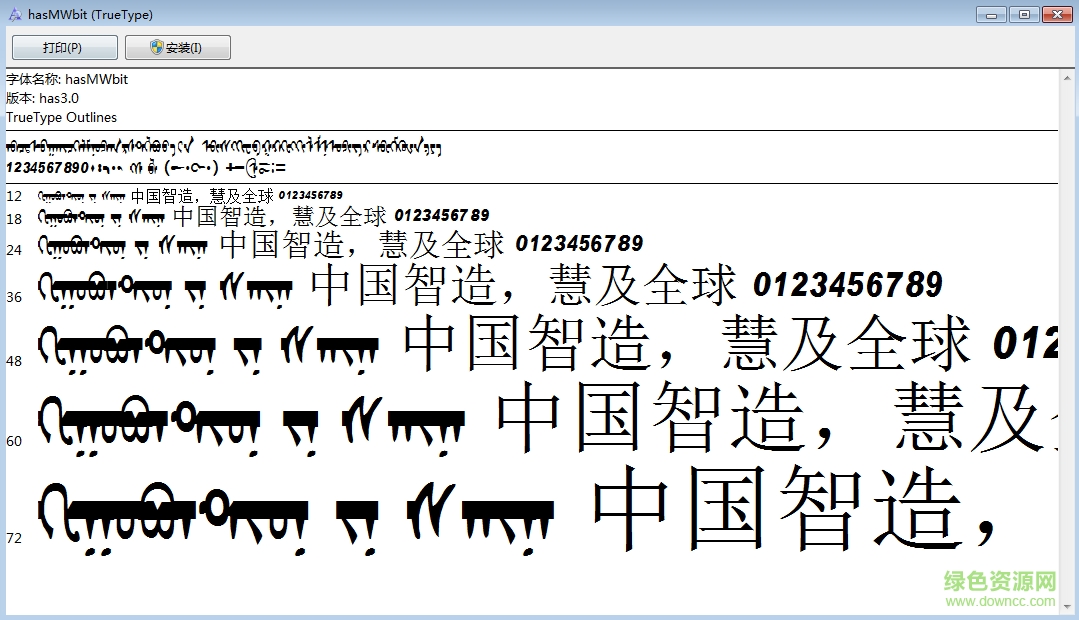
hasmwbit字體
hasmwbit是一款蒙文字體,獨(dú)有的加深讓蒙文輸入更加深沉大氣,專為蒙古人打造,喜歡的朋友快來(lái)綠色資源網(wǎng)免費(fèi)下載吧!
hasmwbit字體介紹
hasMWbit字體家族系列主要提供Regular等字體風(fēng)格樣式,共有110個(gè)字符。
hasMWbit英文字體